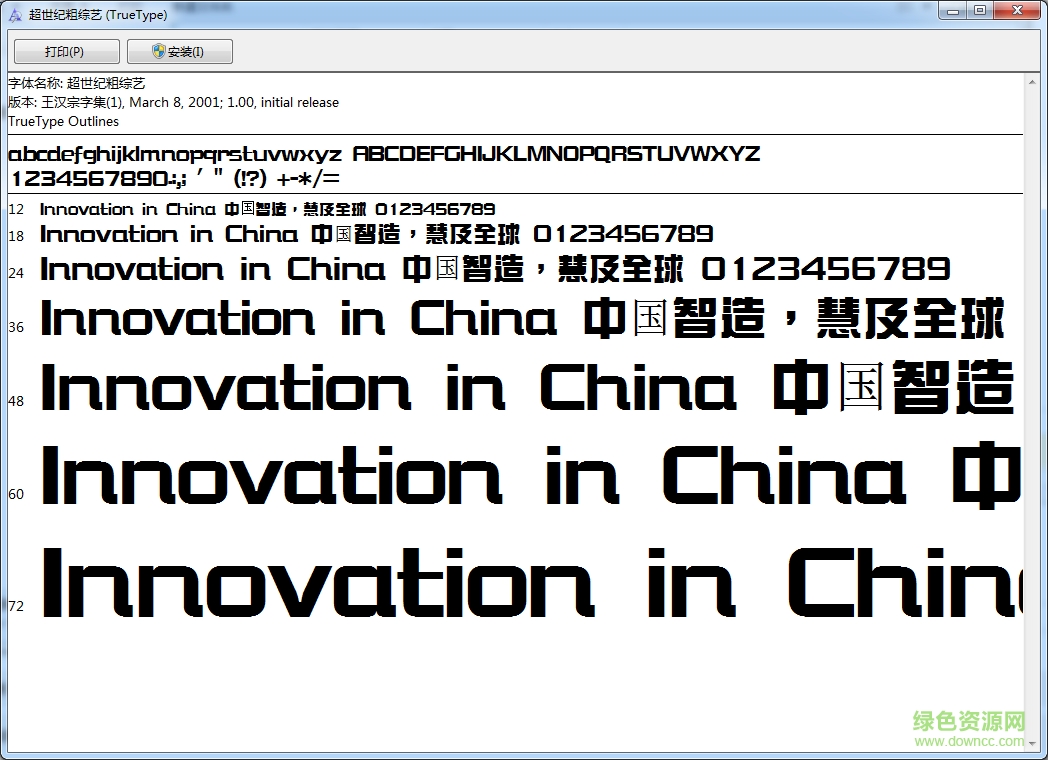
超世紀粗綜藝是一款獨具特色的是超世紀字體軟件,字體簡潔美觀大方,字體在很多領域應用都特別的廣泛,使用非常便捷。有需要使用這款字體的朋友快來綠色資源網(wǎng)下載體驗吧!
超世紀粗綜藝是超世紀字體庫中的一種字體,字體威武有形,力道十足,可應用于繪畫設計、雜志報刊、平面廣告、印刷包裝等領域,喜歡的朋友可免費下載收藏。